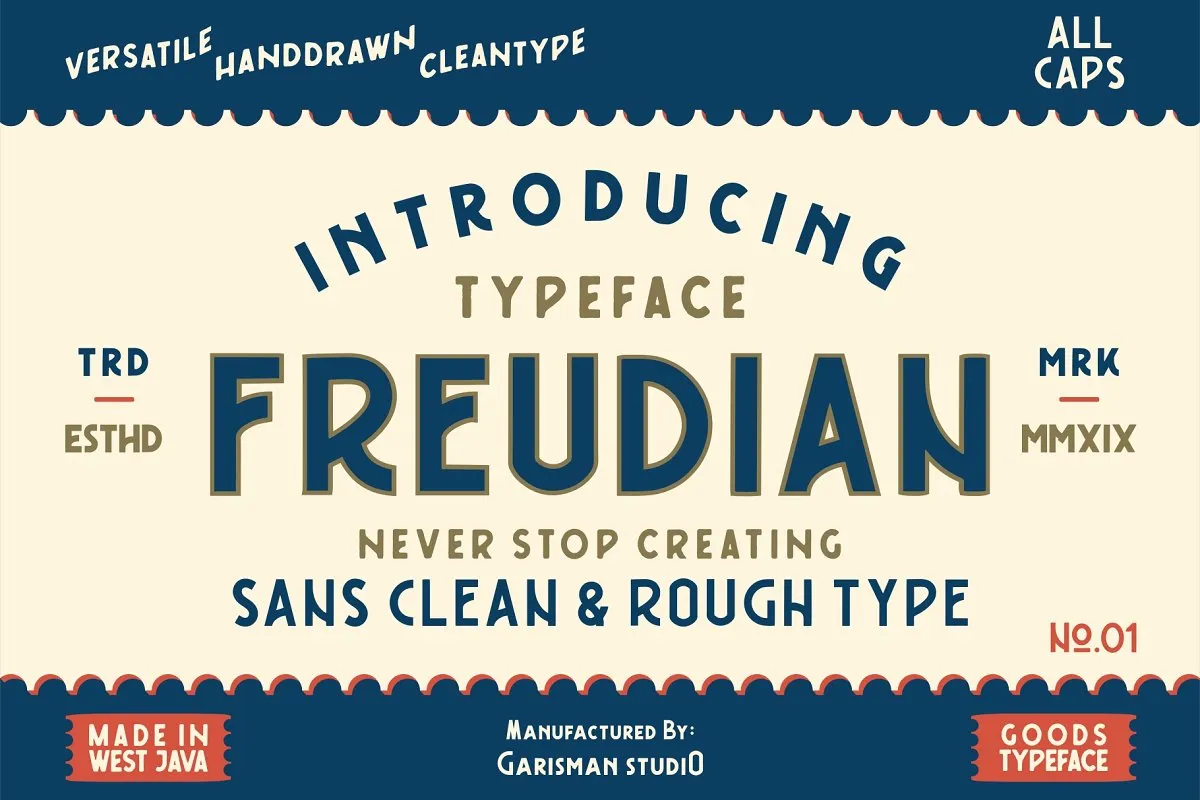
Freudian Typeface – Download Grátis
A Freudian Typeface é uma escolha perfeita para quem busca elementos retrô e handmade em suas criações gráficas. Este tipo moderno de linhas retas ganha um toque vintage ao ser observado mais detalhadamente, com formas simples que remetem a designs antiguidade dos anos passados. Ideal tanto para projetos de logotipos quanto para materiais de marca ou impressões em série como cartões de visita e posters, esta fonte também é perfeita para aplicar na fotografia, frases de incentivo e camisetas personalizadas. Se você busca dar um toque vintage a seus trabalhos gráficos sem deixar de manter a elegância do tipo de linha reta, a Freudian Typeface é uma opção imperdível.